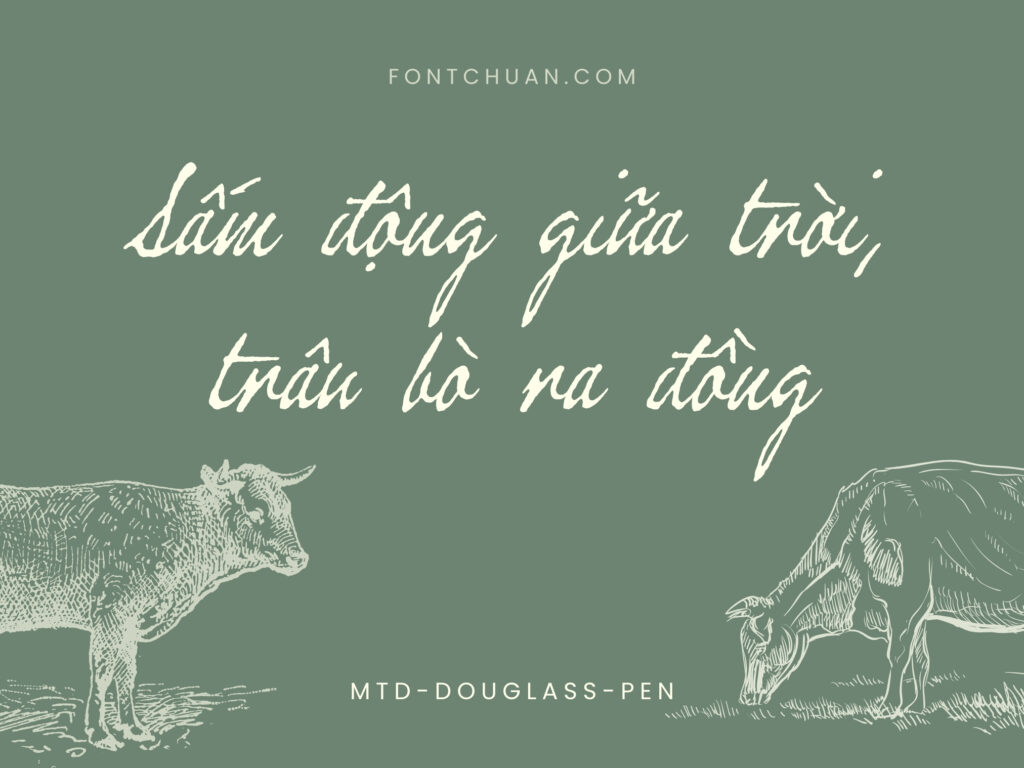
Font MTD Douglass Pen Việt Hóa
Tác giả Font: Three Islands Press
Font MTD Douglass Pen là một kiểu chữ viết tay lịch sử, được thiết kế dựa trên chữ viết tay của Frederick Douglass, một nhà cải cách xã hội và lãnh đạo phong trào bãi nô thế kỷ 19. Font này đã được Việt hóa bởi Mộc Hạ, hỗ trợ đầy đủ tiếng Việt cùng hơn 90 ngôn ngữ khác, mở rộng khả năng ứng dụng trong các thiết kế đa ngôn ngữ. Đây là một trong những phông chữ được cộng đồng thiết kế đánh giá cao và sử dụng trong nhiều dự án sáng tạo, đáp ứng nhu cầu đa dạng của người dùng.
MTD Douglass Pen nổi bật với các đường nét mạnh mẽ và phóng khoáng, tạo cảm giác cổ điển và trang trọng. Font rất phù hợp cho các thiết kế liên quan đến văn hóa, lịch sử, giáo dục, cũng như các tác phẩm văn học và thư pháp. Các ngành nghề phù hợp bao gồm quảng cáo, giáo dục và công nghệ. Font này cũng lý tưởng cho các sự kiện như Tết, Giáng sinh, Valentine và các lễ hội khác.